디자이너 집중탐구 인터뷰
그래픽 디자이너와 폰트회사 그리고 폰트의 신세계 Mix폰트
폰트디자인 업계에서 폰트를 제작하지 않는 23년 차 그래픽 디자이너. 처음 폰트 업계에 발을 들여놓은 건 폰트회사의 홍보기획실에 입사하면서부터다. 폰트 제작 이외에 폰트를 이용한 인쇄물, 타이포그라피 전문지 '정글'과 '디자인정글' 웹사이트, 영상물을 디자인하면서 폰트가 디자인에 얼마나 중요한 역할을 하는지 알게 되었다. 이후 패키지, 잡지, 단행본, CI, Web, 등의 디자인을 지속했다. 지금은 폰트릭스에서 폰트 이상의 그 무언가를 생각하고 있다. 현재 그 결실로 폰트회사 중 가장 많은 기술 특허를 보유한 회사의 대표 이사.
그래픽 디자이너가 선택한 폰트디자인회사 창업. 무엇이 그를 이끌었을까. 김재욱 디자이너는 폰트가 모든 분야의 디자인에 기초가 되는 아주 중요한 요소라고 생각했다. 선택한 폰트를 어디에 어떻게 써야 할지는 모든 디자이너에게 가장 큰 고민이고, 폰트(글자)를 잘 다룬다면 편집, 영상, CI.BI 등등 모든 분야의 기본을 갖출 수 있다는 것을 몸소 체험했다. 폰트릭스는 기본형 폰트를 제일 잘 만드는 회사이다. 또한 폰트의 활용을 제일 잘하는 폰트회사라고 자부한다. 폰트 제작을 넘어 폰트를 활용한 암호솔루션, 인감폰트, 채팅용 폰트압축기술, 움직이는 폰트, 칼라폰트, 믹스폰트, 인공지능(AI) 등등의 기술과 특허를 보유하고 있다.
그 중에서도 이번에 홈페이지 리뉴얼을 하면서 재오픈된 믹스폰트(Mixfont) 서비스가 있습니다. 어떻게, 왜 만들게 되었는지.
디자이너들은 폰트를 사용할 때 습관이 있습니다. 예를 들어 한글은 Rix고딕, 영문은 Rix명조, 장평은 90%, 자간은 -50 등등 또한 프로젝트마다 정해진 폰트와 사용법이 각각 존재합니다. 이렇게 복잡한 문제를 한번에 해결하고, 다양한 프로그램(어도비, 오피스, PPT…등등)과 문서에서 편하게 사용할 수 있는 것을 생각했습니다. 믹스폰트를 통해 작업 효율이 높아지고, 작업 시간은 단축되는 효과를 기대하며 기획하게 되었습니다. 믹스폰트는 앞으로 더 효율적으로 발전할 것입니다.
디자이너로서 믹스폰트를 가장 잘 활용하는 방법, 이렇게 사용하면 좋다 추천해 주신다면.
첫 번째로는 개인별로 믹스폰트 만들기, 내가 잘 사용하는 기본형 폰트를 만드는 방법입니다. 폰트의 자간, 장평 등을 조절하여 내 이름 폰트명 [Mix홍길동]으로 폰트를 만들고 사용합니다. 두 번째로는 프로젝트별로 믹스폰트를 만드는 방법인데 팀원들이 공통된 작업을 하기에 적합합니다. 예를 들어 행사 작업물인 경우 폰트명을 [Mix가을축제제목용, Mix가을축제본문용] 이렇게요. 세 번째로는 우리 회사, 우리 가족, 우리 학교만의 전용서체를 만드는 방법입니다. 전용서체는 대기업에서나 제작하는 것으로 알고 있지만 Mix폰트를 이용해 제작한다면 비용과 시간을 절약할 뿐만 아니라 폰트의 완성도 또한 보장받을 수 있습니다. [Mix서울대, Mix대한전자, Mix지안이네….]
그럼 믹스폰트에 대해 좀 더 자세히 알아볼까요
릭스폰트의 MIX폰트 서비스는 내 맘대로 원하는 폰트들을 조합하여 나만의 폰트를 만들 수 있는 정말 재밌고 유용한 서비스 중 하나라고 생각되는데요, 사용 방법을 어려워하시는 분들이 많아서 쉽고 상세히 알려드리고자 합니다. 그럼 팔로팔로미!
#1 원하는 폰트로 미세조정까지!
먼저 릭스폰트 홈페이지 메인 화면 카테고리에서 MIX폰트를 클릭해 주세요.
아래와 같은 화면이 뜨면 이제 폰트 DIY를 시작할 준비가 되었습니다.
한글, 영문, 숫자, 한자 순서로 되어있는 배너에서 각각의 원하는 폰트 종류, 굵기 등을 선택할 수 있습니다.
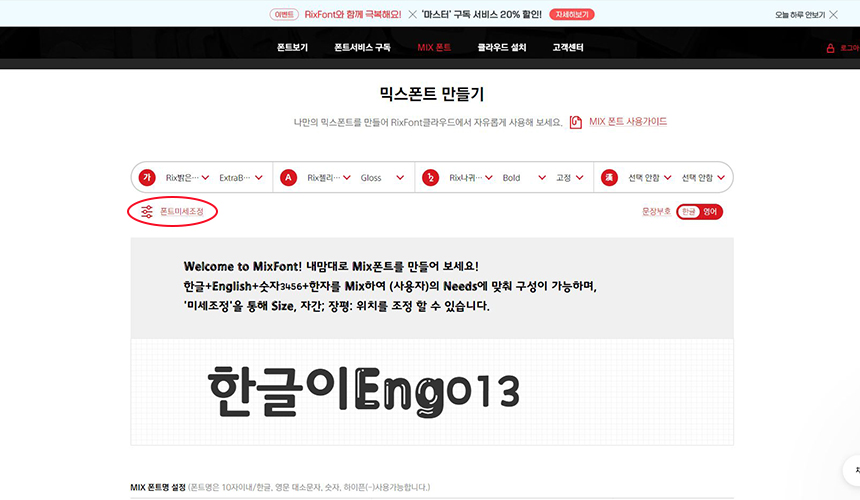
예시로 만들어보고 싶은 폰트 조합을 선택해 보았는데요, 한글은 'Rix밝은고딕', 영문은 'Rix젤리튜브', 숫자는 'Rix나귀엽냐옹'을 선택한 후 각각의 굵기도 어울리게 조절해 주었습니다. 영어에 쓴 젤리튜브 폰트는 글로스 효과로 포인트를 주었고요. 전체적으로 둥글둥글 귀엽지만 가독성 좋게 만들어 봤어요 ღ'ᴗ'ღ
여기서 끝이 아닙니다~ 아주 중요하고 유용한 꿀팁 기능인 폰트미세조정 클릭!
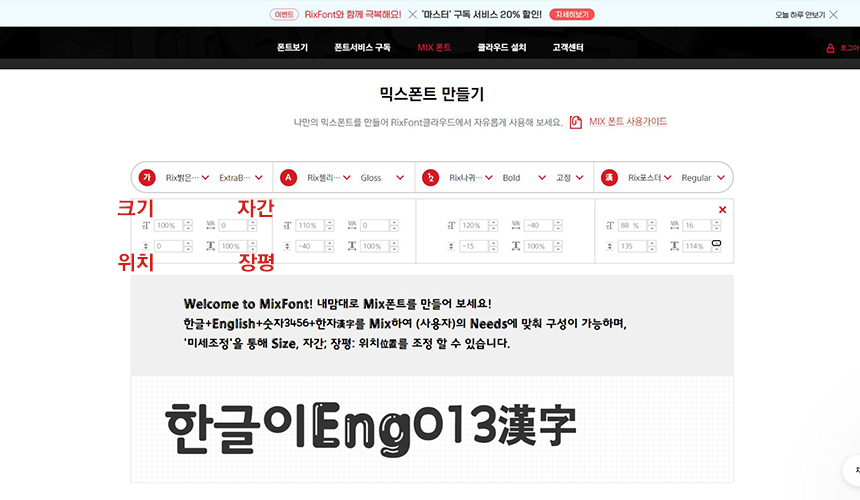
폰트미세조정을 클릭하면 위와 같이 각 폰트별로 크기와 위치, 자간, 장평을 설정할 수 있습니다.
각각의 다른 폰트들을 조합하는 것이기 때문에 크기나 위치가 뒤죽박죽일 수 있는데 굉장히 세세한 조정을 할 수 있답니다. 보통 한글보다 크기가 작은 영어와 숫자는 크기를 키워주고 위치, 자간을 조절해서 한글과 잘 어우러지게 맞춰주었고요, 또 한문도 'Rix포스터' 폰트를 선택해 숫자와 어우러지게 폰트미세조정을 해주었습니다.
#2 내 맘대로 폰트명 만들기
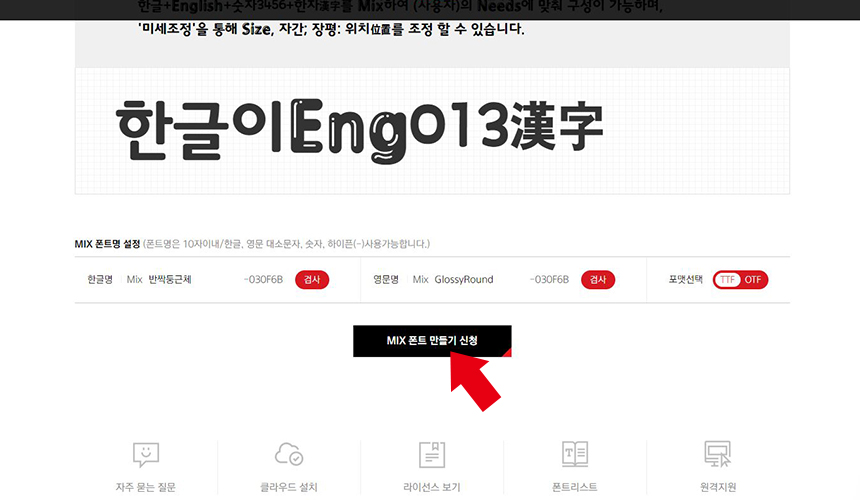
#3 효율성 업! 공유하기
완성된 폰트는 '공유하기'를 통해 프로젝트를 함께 하는 직장 동료, 진행 중인 거래처, 친구, 지인 등과 공유할 수 있는데요.
팀 프로젝트 시 동일한 서류 양식에 일관된 폰트로 작업해야 할 때 공유하기! >>폰트명 [Mix한글프로젝트02]
PPT 과제 만들 때 팀원들과 사용할 폰트 정해서 공유하기! >>폰트명 [Mix세계속의한글PPT]
넘나 유용하겠지요?!
#적용해봄
한 번의 클릭으로 내가 선택한 한글 폰트와 영문 폰트가 자동으로 적용되는 것을 볼 수 있습니다. 넘나 편하고 효율적인 것!